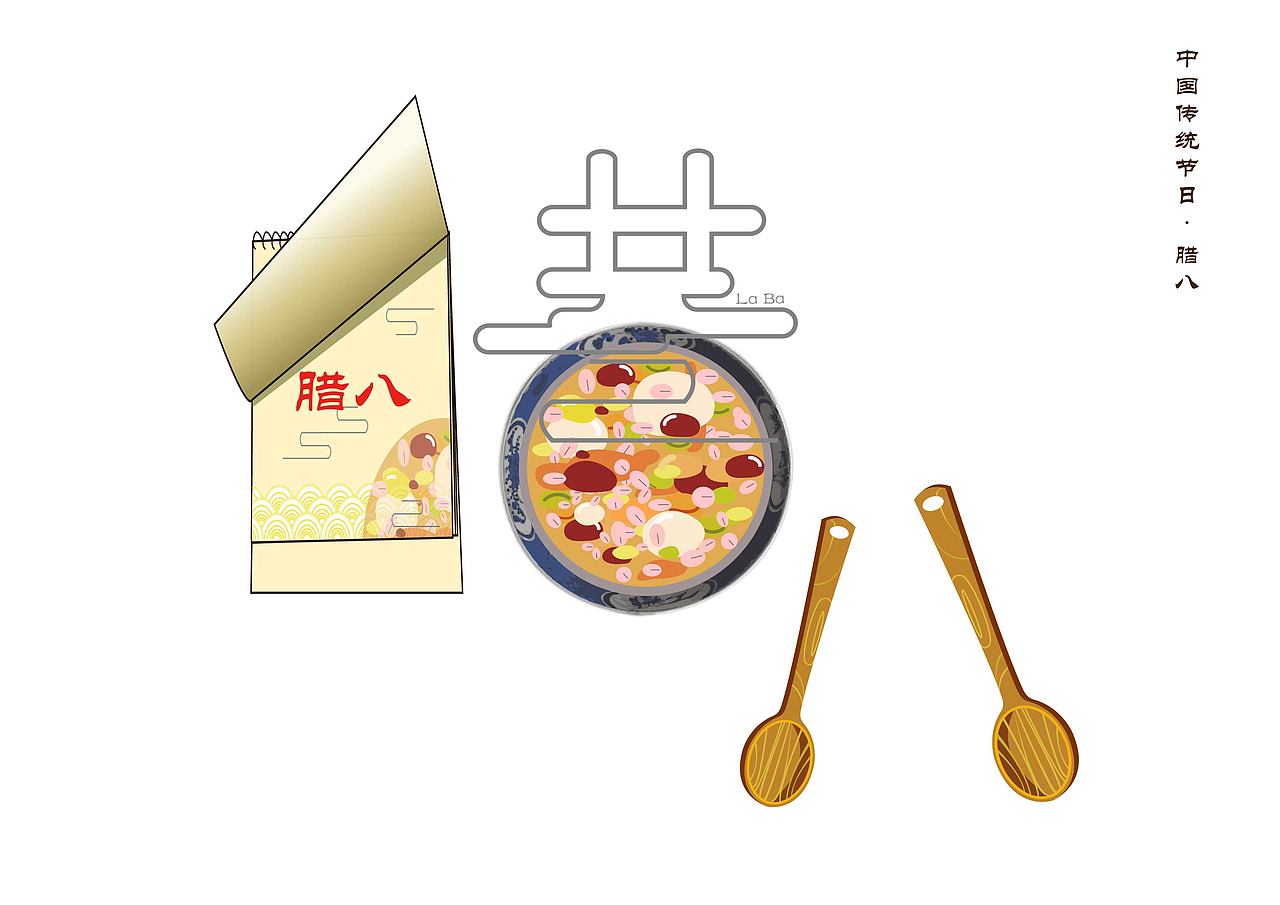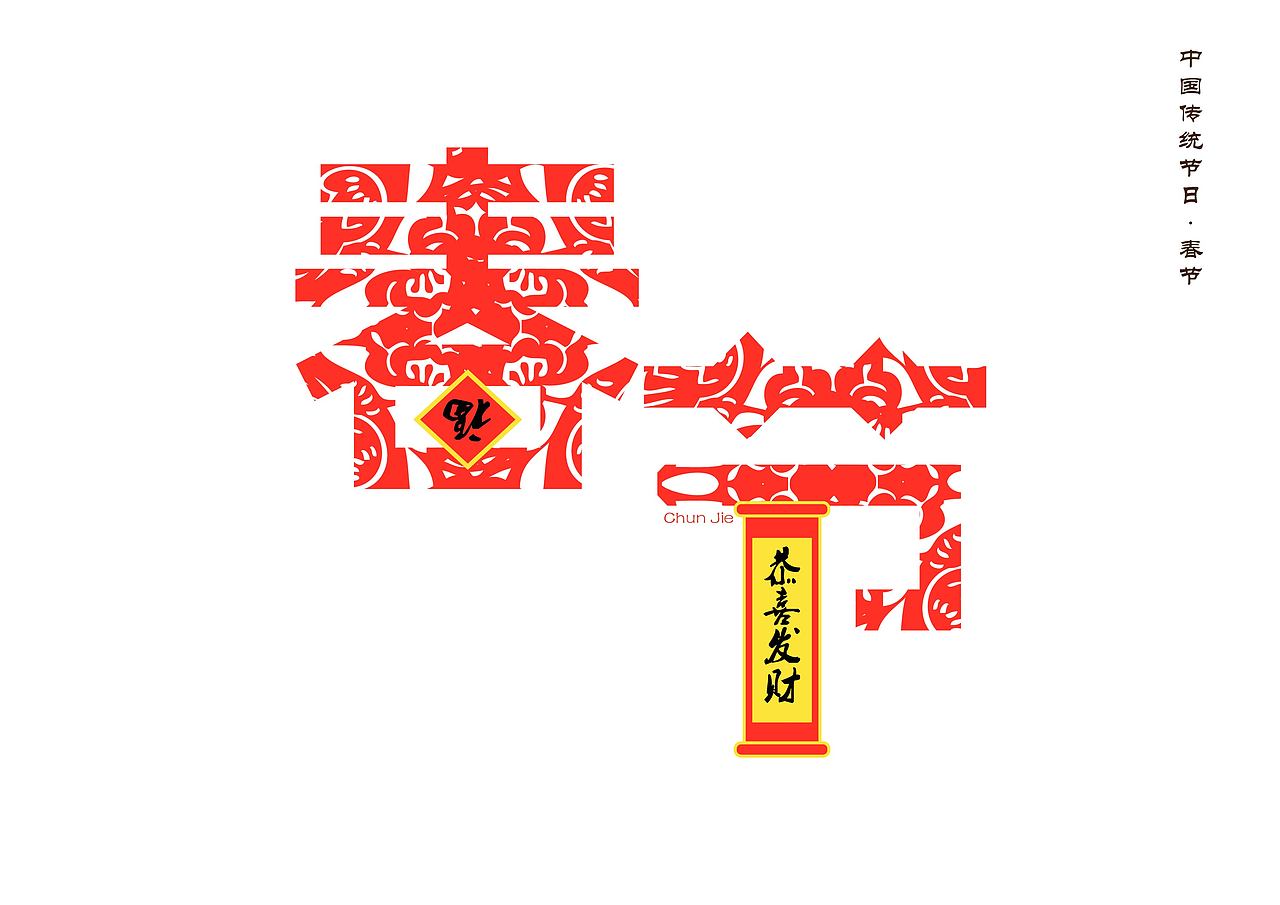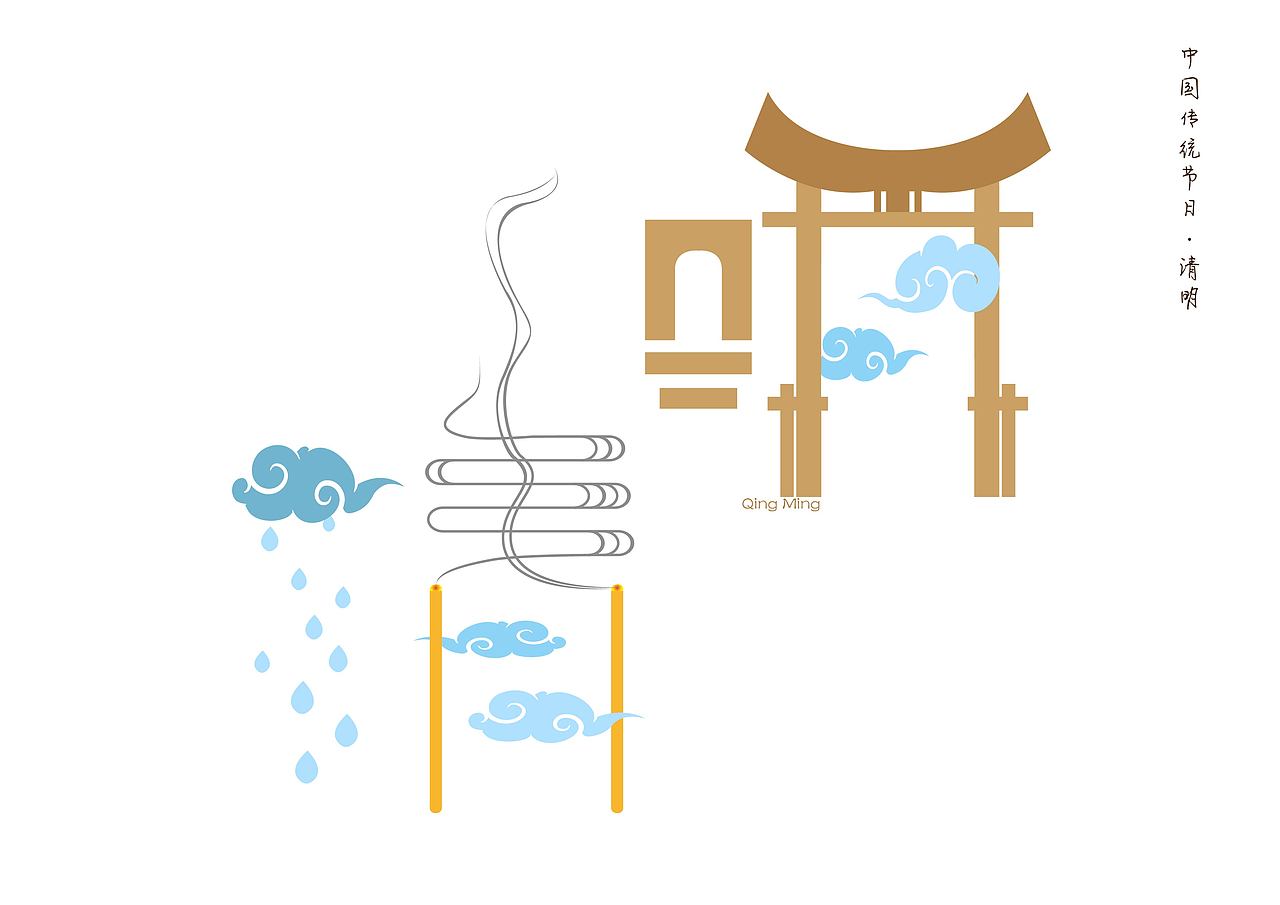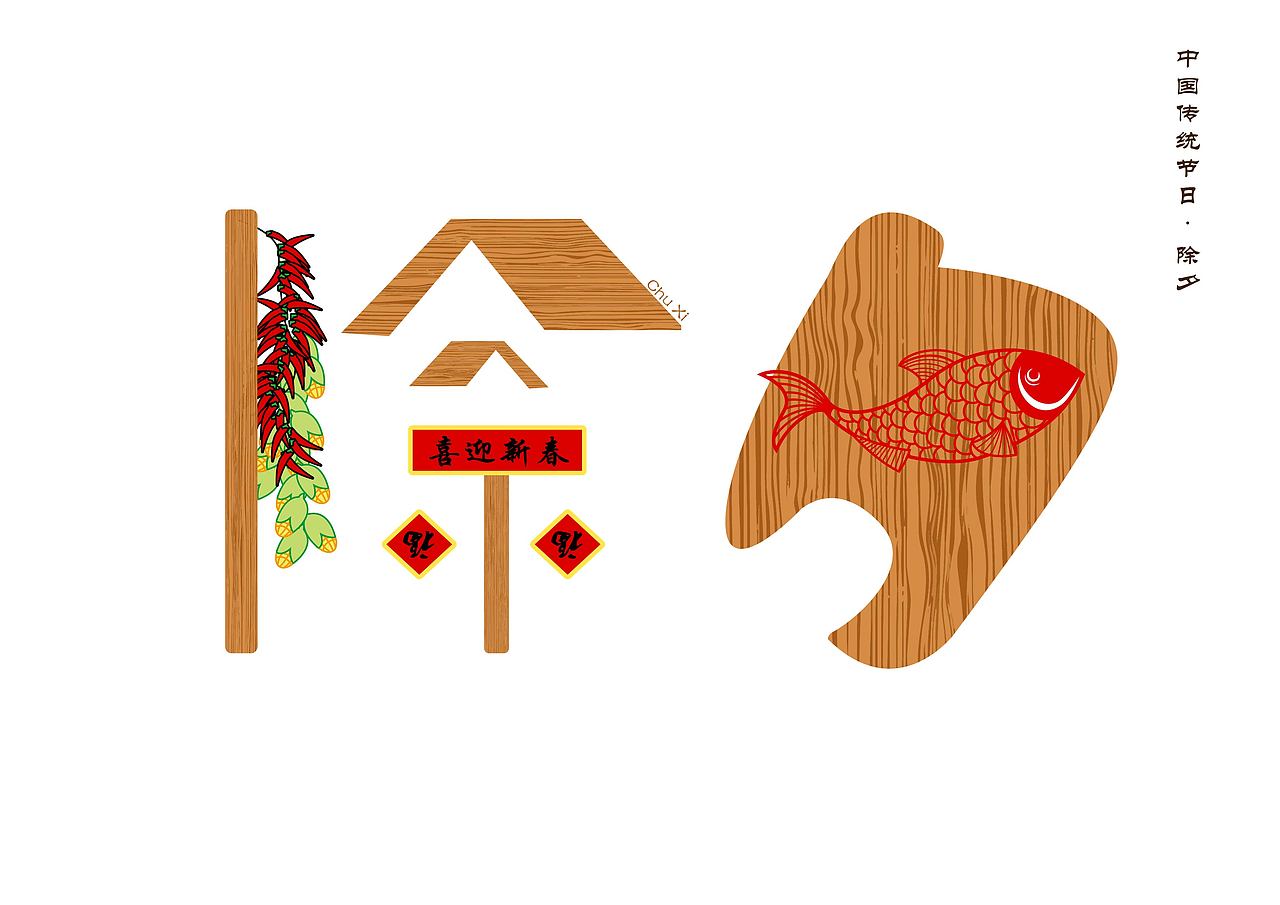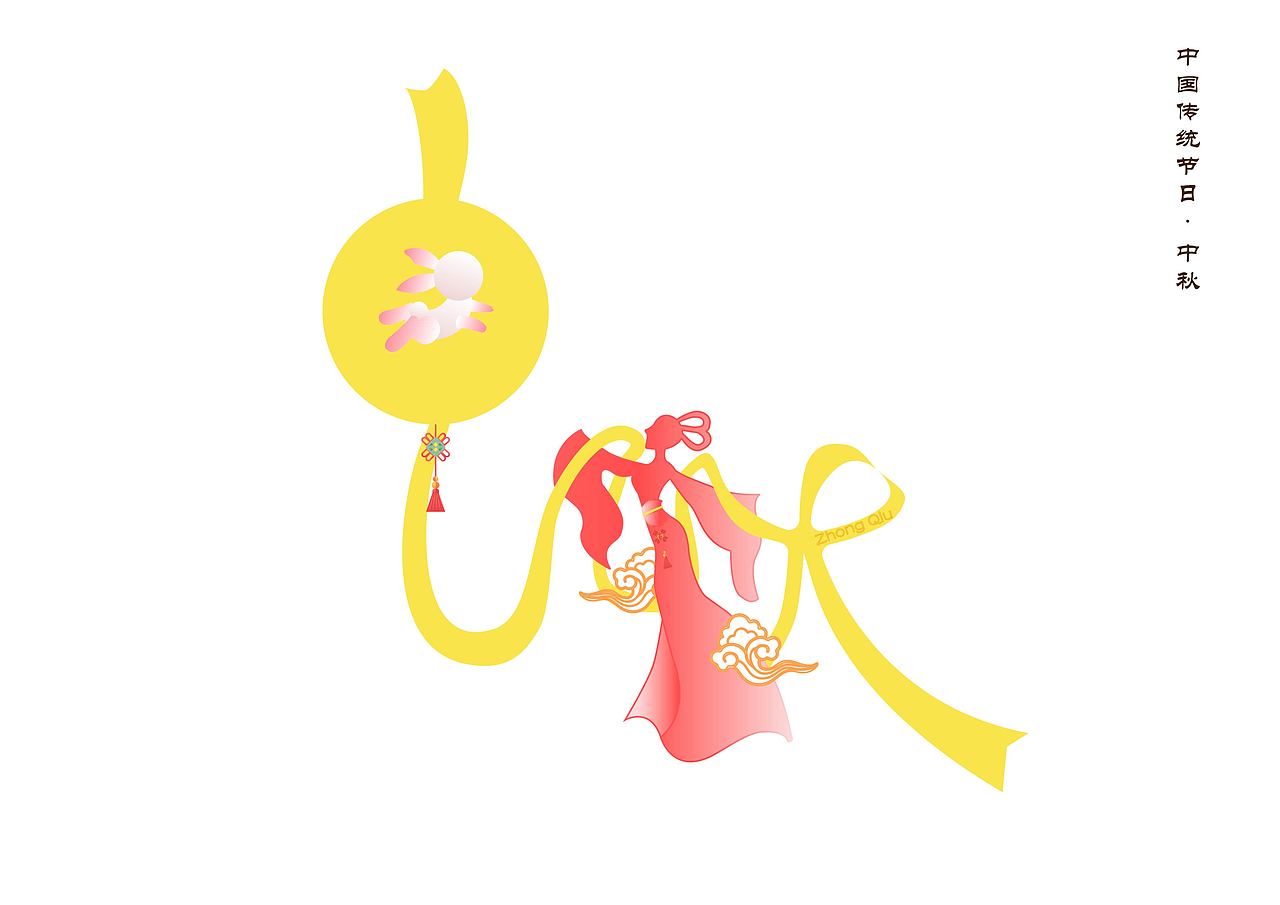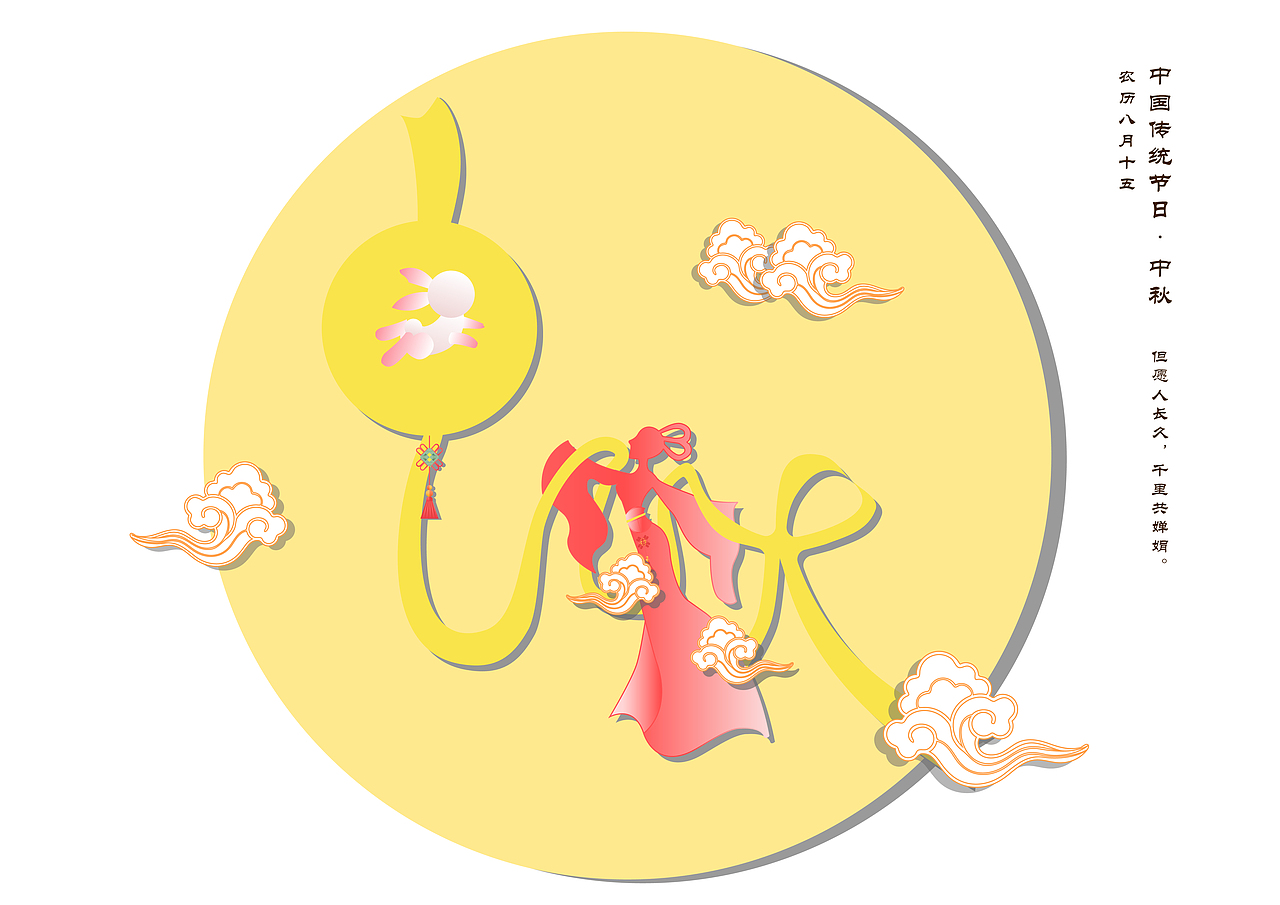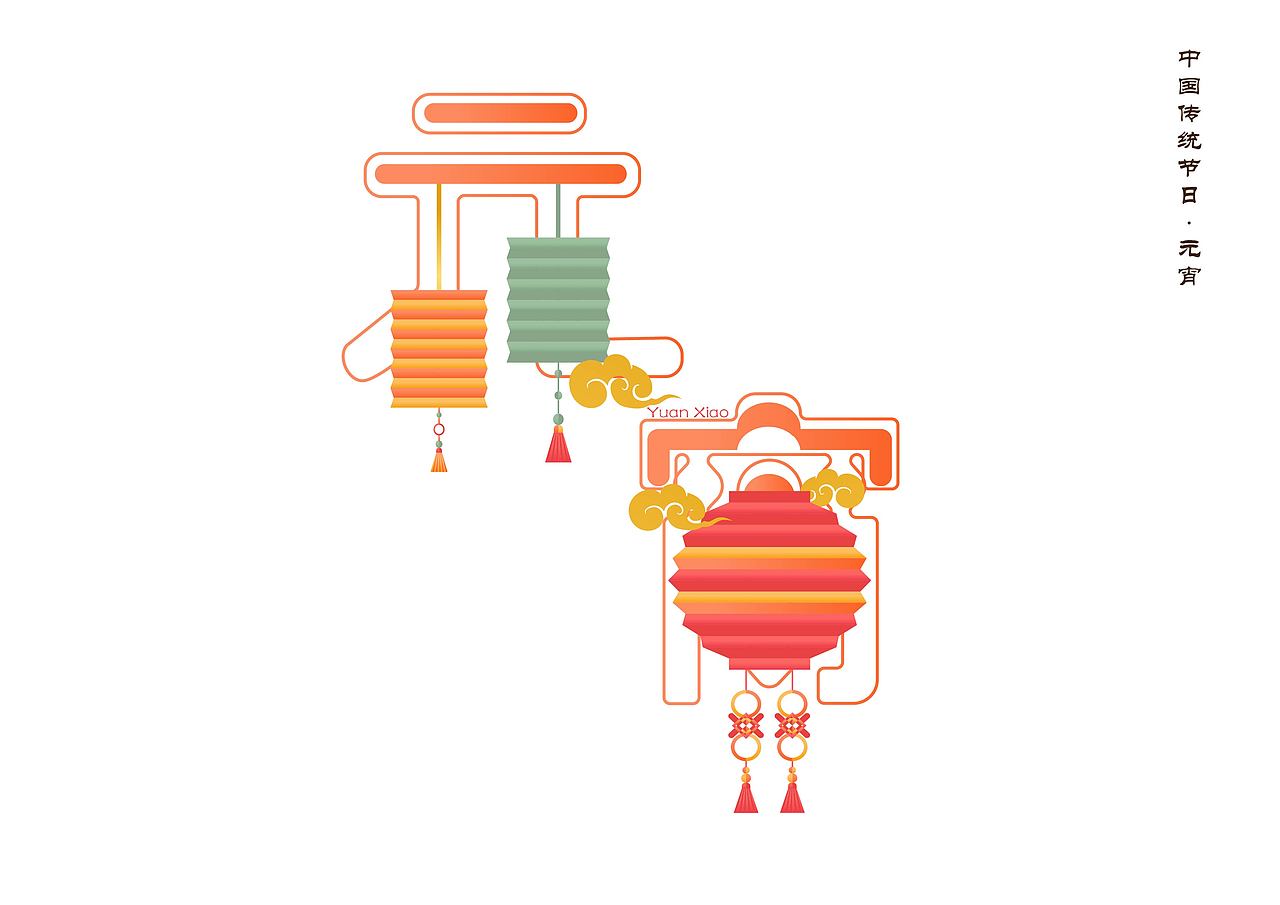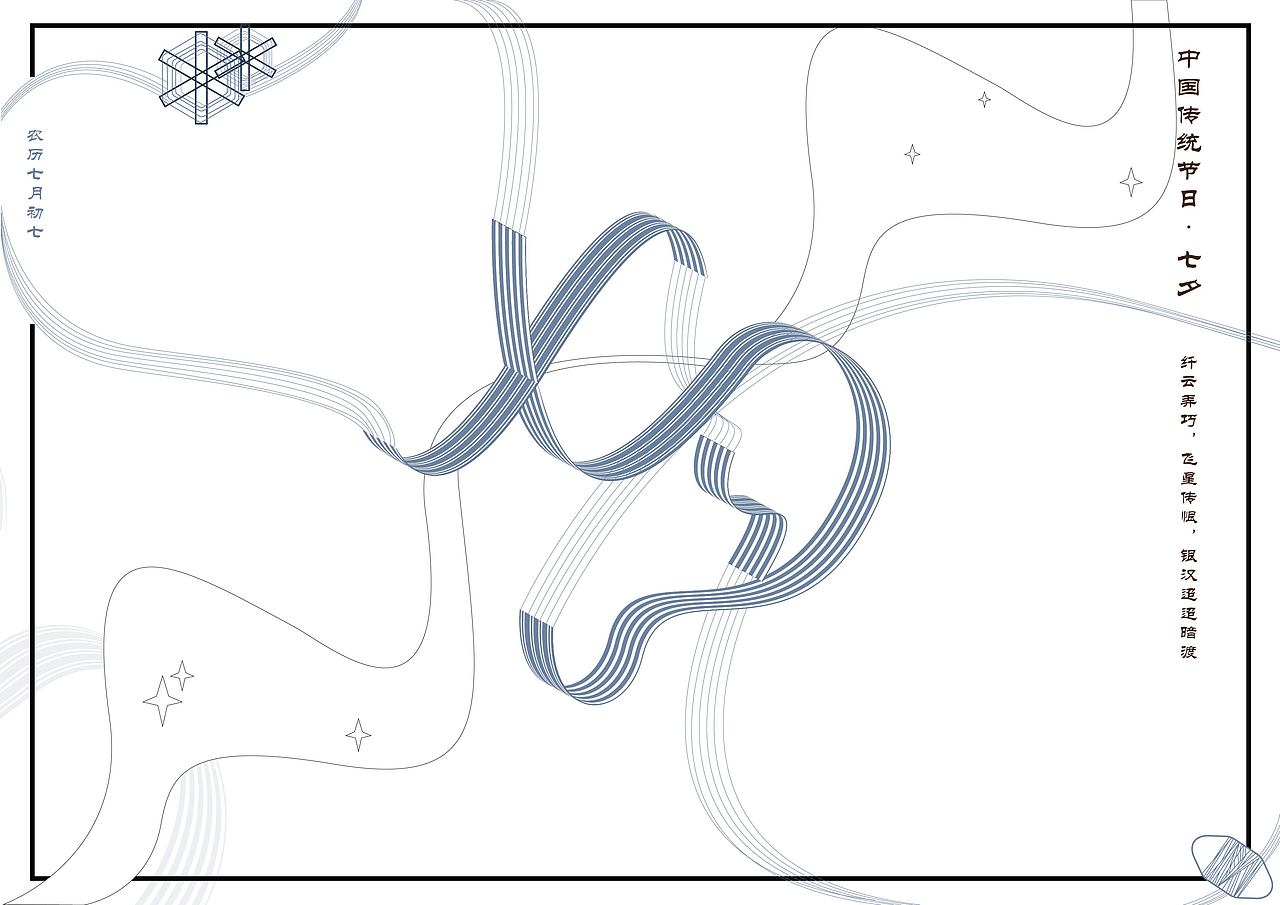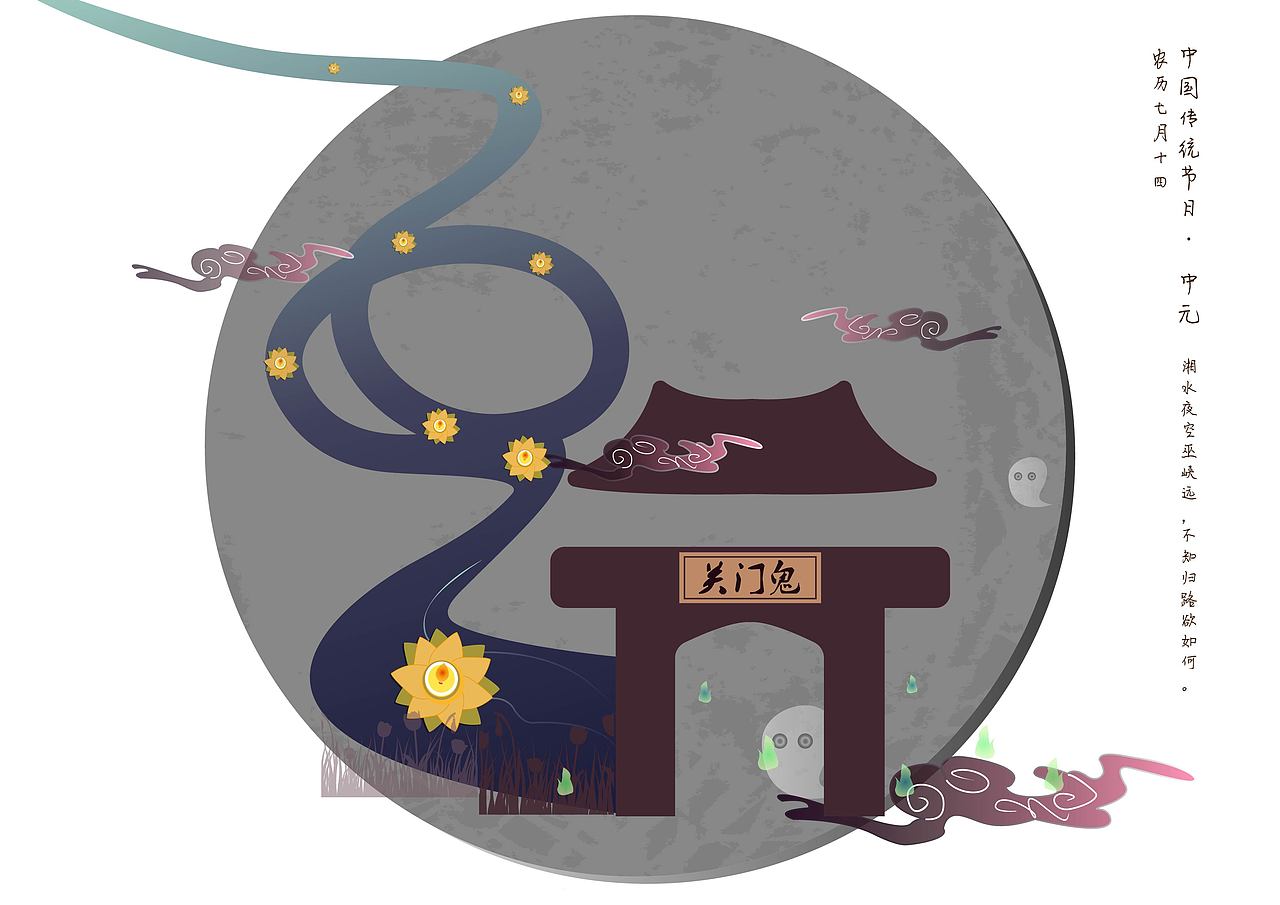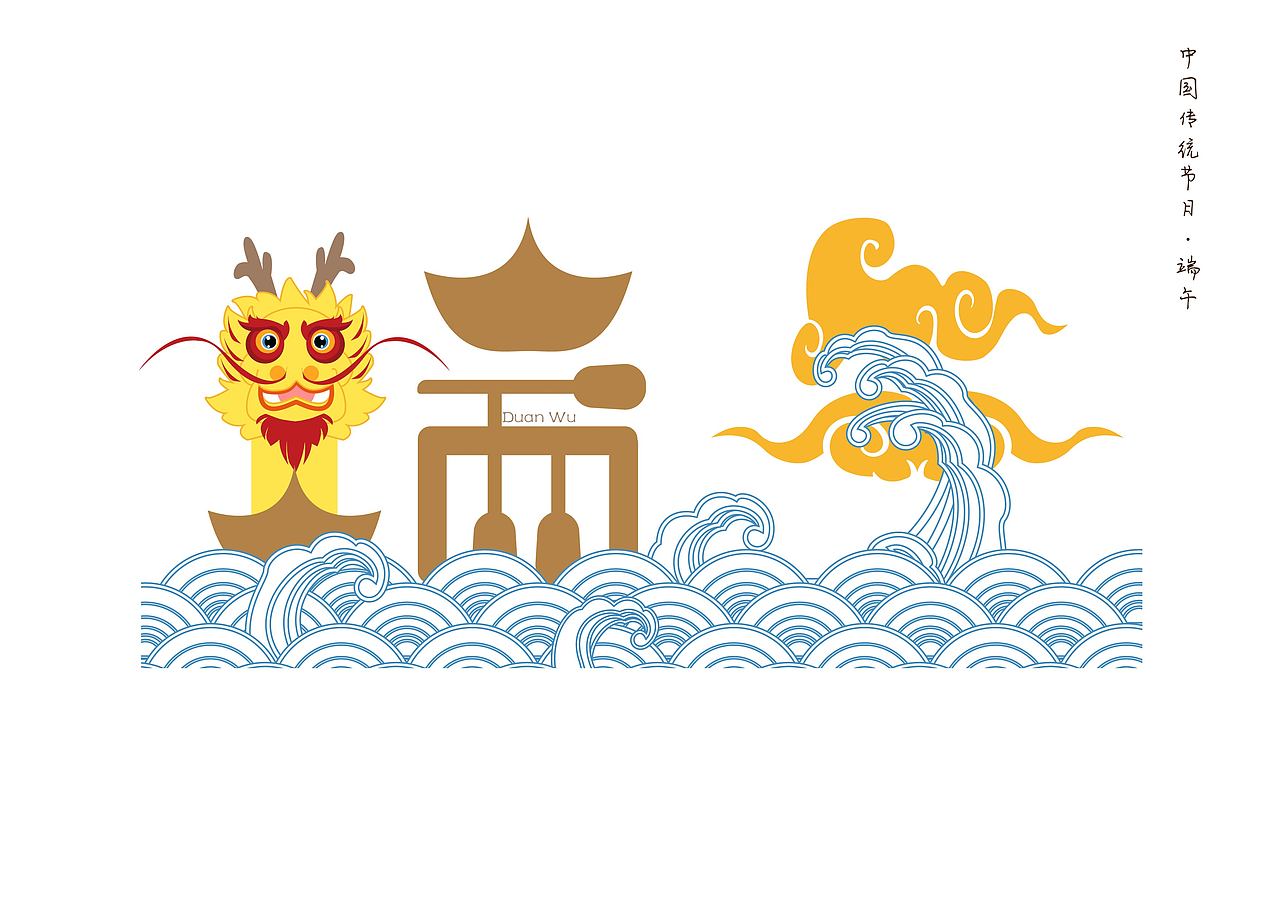
中国传统节日字体创意设计
我选的毕业设计题目为中国传统节日字体创意设计,在此次毕业设计中,根据对创意一词的理解结合中国传统节日及对汉字字体设计的研究,选取了春节、元宵、清明、端午、七夕、中元、中秋、腊八、除夕这九组传统节日进行字体创意设计。在字体设计中,一个文字是由横、竖、点、撇、捺、折弯勾等笔划形态来构成的字体,要如何对其笔划结构与图形元素进行组合变化,创造出有趣生动的字体设计,把所要表达的内容直接鲜明地展现出来是此次设计的重要内容。希望此次设计能够引起人们对中国传统文化的重视,并能够更好的延续与发展下去。
春节——中国最为盛大又热闹非凡的传统节日。根据黑体的字形结构笔划进行变化拼合,其配色主要用红色与黄色,给人们视觉感官传达活力积极的感觉,象征着繁荣幸福。
元宵——节日风俗有赏灯、猜灯谜、耍龙灯、出门赏月、共吃元宵等活动,元宵两字则取其灯笼作为其主要图形元素进行制作,根据其字形笔划进行图形的拼接组合,更直接地让人理解其文字图形所表达的内容,背后进行了元宵二字的字形框架,是为避免其画面元素过于简单而添加的,其配色主要用同色渐变及暖色调,显得画面热闹且富有活力。
清明——是中国传统节日之一,其节日风俗主要是祭奠先人,清明两字则取其节日意义扫墓祭祖以及节日谚语“雨打清明前,春雨定频繁”为主进行元素提取创作,清明的“清”字的偏旁三点水用云及雨水来表达,“清”字的“青”则用香火来替代,“明”字偏旁“日”用拱门元素替代,而“明”字的“月”则用古时候的牌楼门口来进行图形替代,其云的位置前后错落替代其中的笔划结构,使得画面生动,其颜色色调主要体现素雅,给人以宁静而平稳的感觉,进而组成了清明这般有趣而又简明的画面。
端午——其节日风俗有赛龙舟、端午食粽、挂艾草菖蒲等,其中要数赛龙舟最为热闹,端午两字则取其赛龙舟的风俗活动为主进行图形元素创意组合,根据其笔划结构形态进行字体的分解重构,端午的“端”字用的是龙头以和侧面的船只以及划龙舟用的桨来表达,端午的“午”则用祥云和翻腾上来的浪花来表达,其配色主要黄色和红色及船只的颜色为主以表达此节日的内敛古韵。
七夕——其一“七夕”我用玉佩作为主要图形元素进行创意设计制作,以情人节为主进行元素提取,古人以玉佩为定情信物,其配色参考了实物玉佩的颜色进行同色渐变色的调和。
七夕——其二是以乞巧为主进行元素的提取的设计,姑娘们到了农历七月初七就会将瓜果放在桌子上跪拜祈求像织女那样心灵手巧,聚集在一起用各种各样的方式比谁更心灵手巧,最常见的穿针引线比巧,“七夕”两字取其纺锤织布为主进行元素提取设计,颜色主要用蓝色,给人恬静沉稳的感觉。
中元——俗称鬼节,节日风俗有放河灯、祭祖、祀亡魂、焚纸锭等,中元二字取其放河灯、鬼门为主进行图形元素的提取创作,中元的“中”字便是取其河流与河灯作为图形元素进行组合,中元的元“字”则用鬼门的图形元素来表达,根据其笔划结构对其进行整合拼接,中元节毕竟是祭祀亡魂的所以配色上除了亮起来的河灯其他的图形元素所以的配色都较深,以符合此节日深远的历史以及其蕴含的神秘色彩。
中秋——这一天有弄月、吃月饼的风俗习惯。中秋两字则取其民间传说嫦娥奔月的故事进行图形元素提取,中秋的“中”字为皎洁的月亮与兔子及嫦娥的披帛组合作为中字,中秋的“秋”字则以嫦娥剪影作为其偏旁,其披帛飘荡出的弧度构成“火”的笔划元素,其配色主要用黄色及红色,其色调较为明亮欢快,以此烘托家人团聚的喜悦之情。
腊八——农历十二月初八是腊八节,腊八两字根据谚语“过了腊八就是年”进行创意图形制作,腊八的“腊”字偏旁“月”用挂历的图形元素来替代、腊的右边笔划结构则用腊八粥以及热气进行替代,而腊八的“八”字为了契合腊八粥则用勺子的元素图形进行替代,其颜色主要用的暖色,以表达此节日的氛围。
除夕——除夕节就是春节的前一天,除夕两字大体所用的是木纹图形元素,门前挂着辣椒和玉米的图形元素代替除夕的“除”字的偏旁部首,用屋顶和对联的横批以及倒福的图形元素来替代其笔划结构,除夕的“夕”字中间的点则用了鱼的剪影来替代,颜色配色主要用红色及原木色的暖调为主,寓意着新年红红火火,年年有余。
中元——系列海报一
中秋——系列海报二
七夕——系列海报三